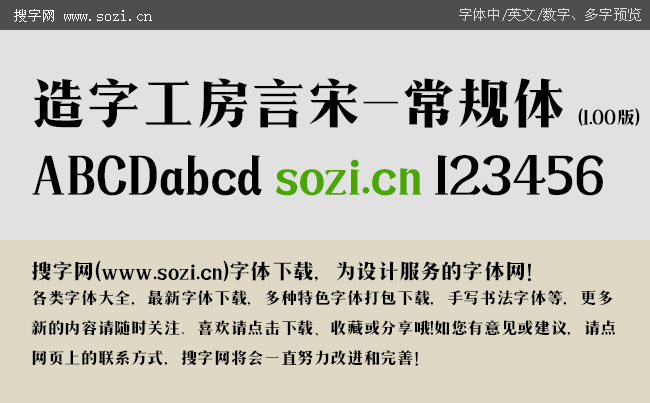
造字工房言宋常規(guī)體
搜字網(wǎng)給大家提供一款很精致的造字工房言宋常規(guī)體字體下載。造字工房言宋體字體字形風(fēng)格典雅,字身緊湊嚴(yán)謹(jǐn),筆畫舒展,橫畫的尖突與勾、點(diǎn)、提的圓潤處理相呼應(yīng),剛?cè)岵?jì)、工整而不失精巧,最大程度的展現(xiàn)筆畫的柔和秀美,有極強(qiáng)的視覺表現(xiàn)力,此款字體適用于報(bào)刊雜志及書籍、畫報(bào)的主副標(biāo)題和個(gè)性品牌設(shè)計(jì)推廣等環(huán)境。